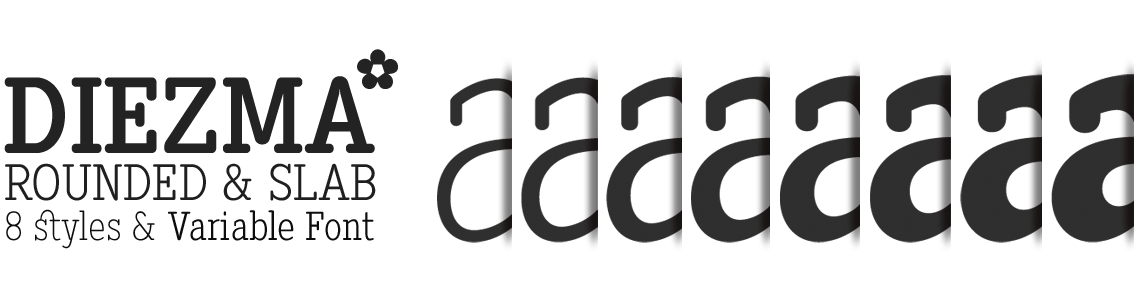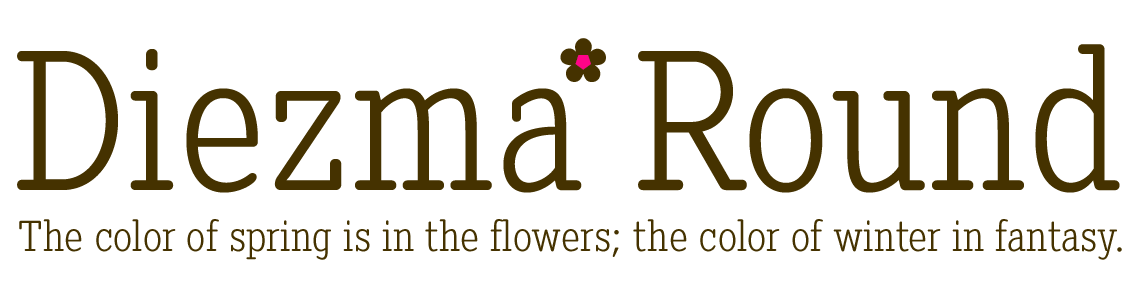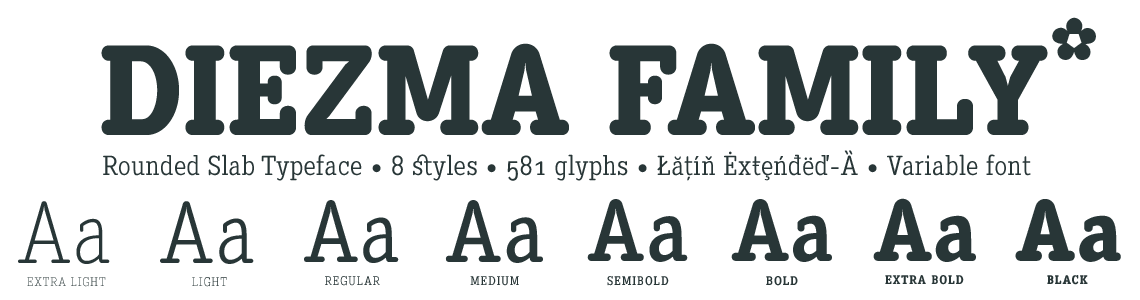
Multipurpose Fonts
Estilo: Rounded, Slab Serif, Geométrica, Corporativa
Proporción: Extra Light, Light, Regular, Medium, Semi Bold, Bold & Black
Glyphs: 581
Funciones OpenType: Additional languages, All Alternates, Alternate Annotation Forms, Capital Spacing, Denominators, Discretionary Ligatures, Extended Fractions, Historical Forms, Historical Ligatures, Inferiors, Kerning, Localized Forms, Numerators, Oldstyle Figures, Ordinals, Scientific Inferiors, Slashed Zero, Standard Ligatures, Subscript, Superior letters, Superiors, Superscript.
La tipografía es ideal para uso corporativo, textos de cualquier tamaño y web. La fuente contiene 581 glifos con funciones OpenType, letras alternativas y un conjunto de caracteres Latin Extended-A y B que admite más de 200 idiomas que usan el alfabeto latino.
Las fuentes Diezma Rd disponen en su versión comercial de un juego de 581 glifos (Latin Extended-A-B), con soporte para cualquier idioma europeo o centro europeo. Diezma Round también incluye funciones OpenType (Compatibles con InDesign, QuarkXpress, Photoshop e Illustrator.